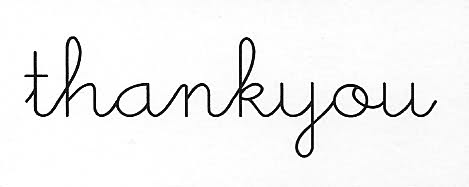
'thankyou' ... kennt jemand diese Schrift
Ich bin in England auf eine schöne Postkarten-Serie gestoßen und frage mich, ob die dort verwendete Schrift auch als Font existiert. Anbei das Beispiel für die thankyou-Karte.
Da das t am Anfang bereits einen Anknüpfpunkt hat, könnte ich mir vorstellen, dass dort eine Schrift benutzt wurde und nicht per Hand gesetzt wurde.